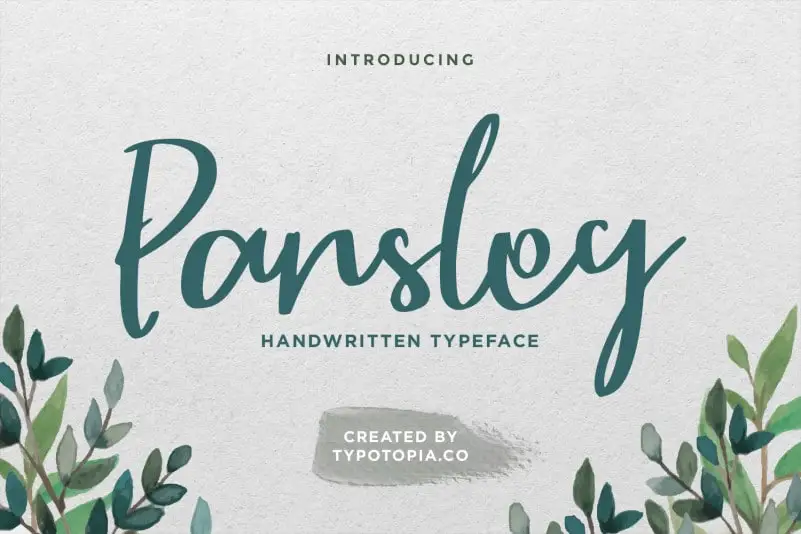
Parsley Script Typeface – Download Grátis
Através da ‘Parsley Script Typeface’, criamos uma nova opção para designers que valorizam a singularidade na sua identidade visual. Este tipo de letra script oferece um toque autêntico e único, perfeito para criar design sofisticado em projetos inovadores como logotipos, cartões de convite, embalagens de produto ou até mesmo roupas. Com o designer typtopia, a ‘Parsley Script Typeface’ traz uma sensação vibrante e emocionante que vai transformar sua próxima criação. Seja em uma identidade visual ambulante como uma camisa, um poster gigantesco ou um cartão de impressão com um quote de autor especial, a ‘Parsley Script Typeface’ está pronta para transformá-lo. Se estiver buscando por uma fonte script que dê vida aos seus projetos digitais e físicos, o designer typtopia trouxe a ‘Parsley Script Typeface’. Seja no mundo dos logotipos, cartões de visita ou até mesmo da moda, a ‘Parsley Script Typeface’ irá capturar seu público.